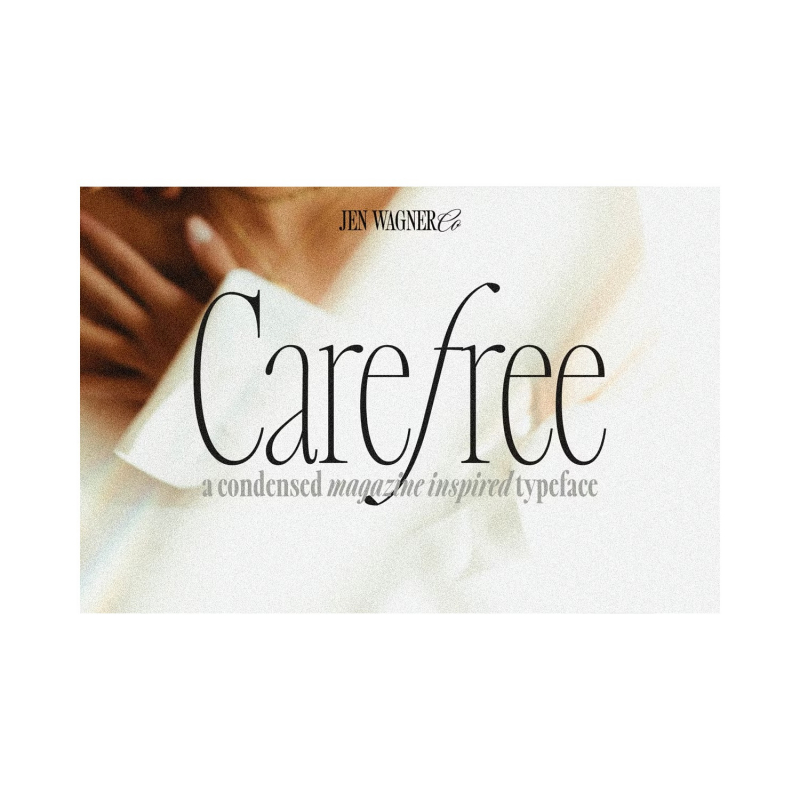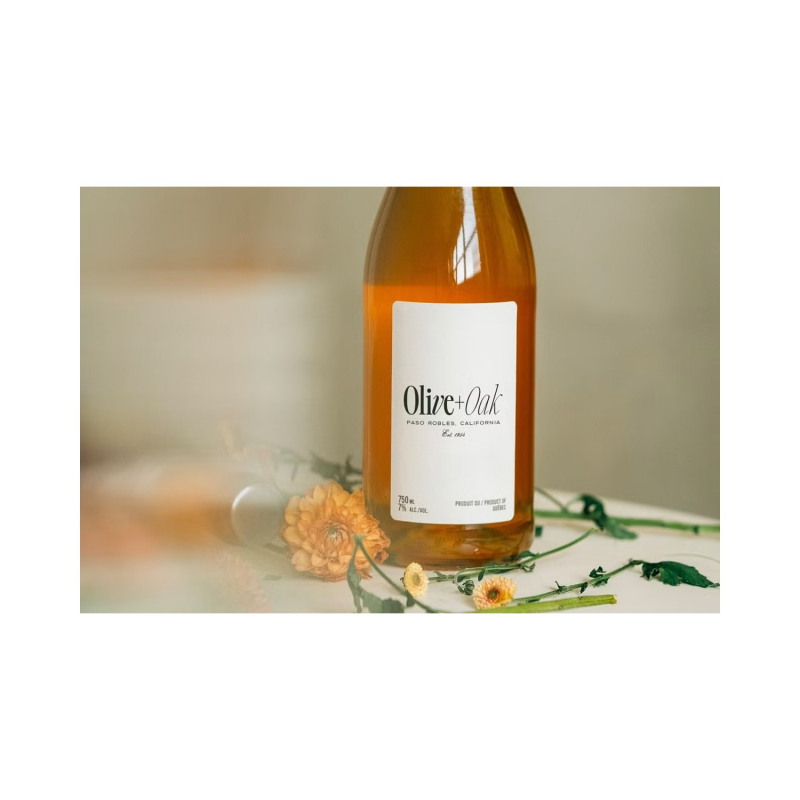
كيرفري | رقيق واضح من 16 خطا
نقدم لك عائلة Carefree Serif - محرف serif مكثف رائع يتضمن 16 خطا ، عاديا ومائلا ، من وزن خط الشعر إلى الخط الغامق.
ومن المفارقات ، أن Carefree كانت واحدة من أصعب الرقيق التي صممتها (لكنها تستحق ذلك!). ما بدأ كتجربة مع مائل حاد الزاوية ازدهر في النهاية إلى العائلة الكاملة التي تراها هنا ، وأنا على رأس الكعب لذلك!
تجعل Carefree من السهل جدا رفع شعار أو نص عنوان ، سواء كنت تريد شيئا جريئا أو حساسا.
يبدو هذا الخط أفضل في الإعدادات الأكبر كنص عرض (فكر في الرؤوس الكبيرة ، والاقتباسات الجميلة ، والعبارات التي تحث المستخدم على اتخاذ إجراء ، وما إلى ذلك) ، ولكن يمكن أيضا أن يكون مذهلا حقا للنص الأطول مثل علامات الاقتباس (انظر الصورة #4). ربما أتجنب استخدام هذا كنص أساسي بسبب التباين العالي.
• إقران الخط: دالاس
• إقران الخطوط الموصى به: Sans الأساسية (بلا ترى هنا وهناك في الصور)